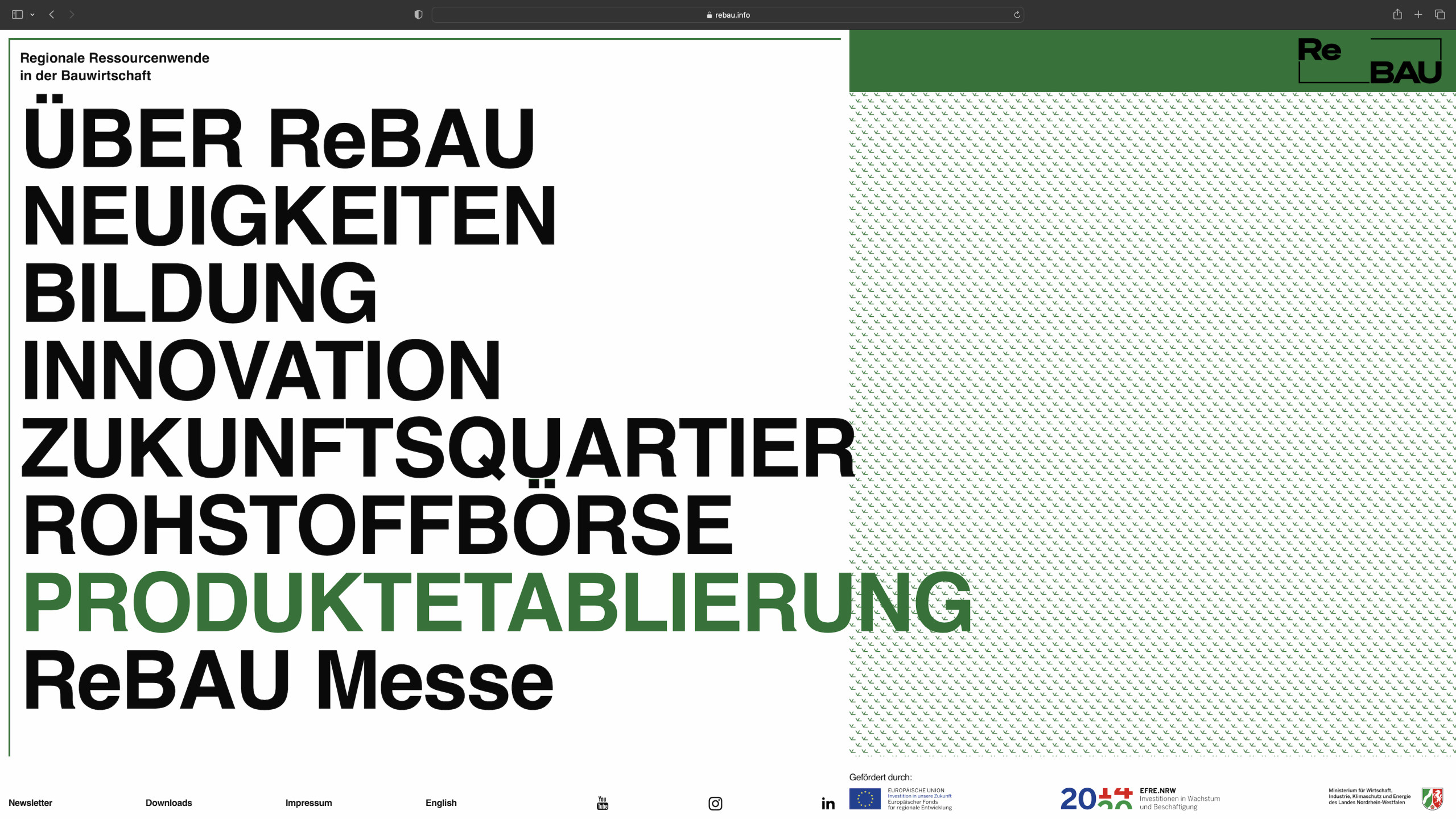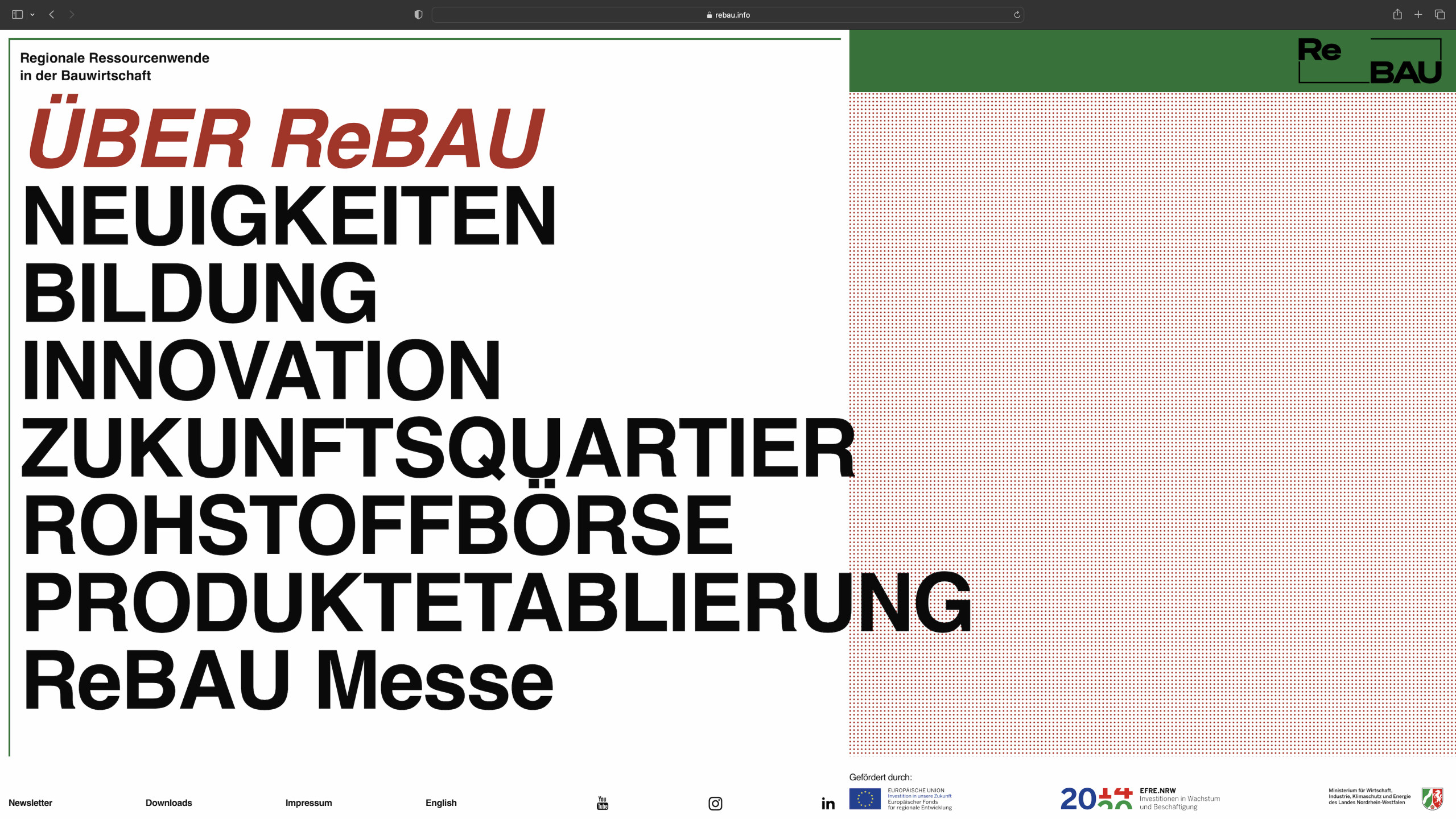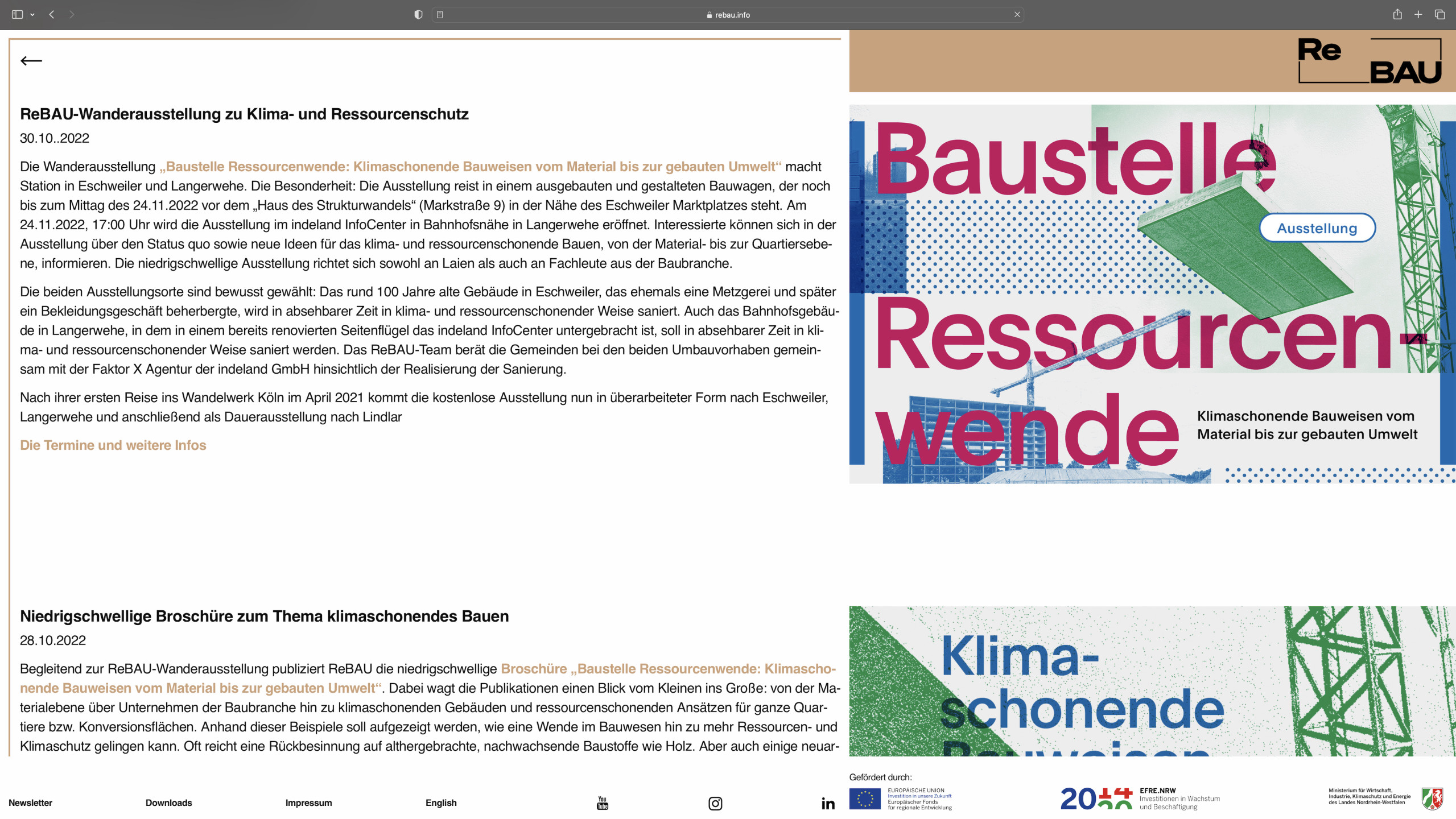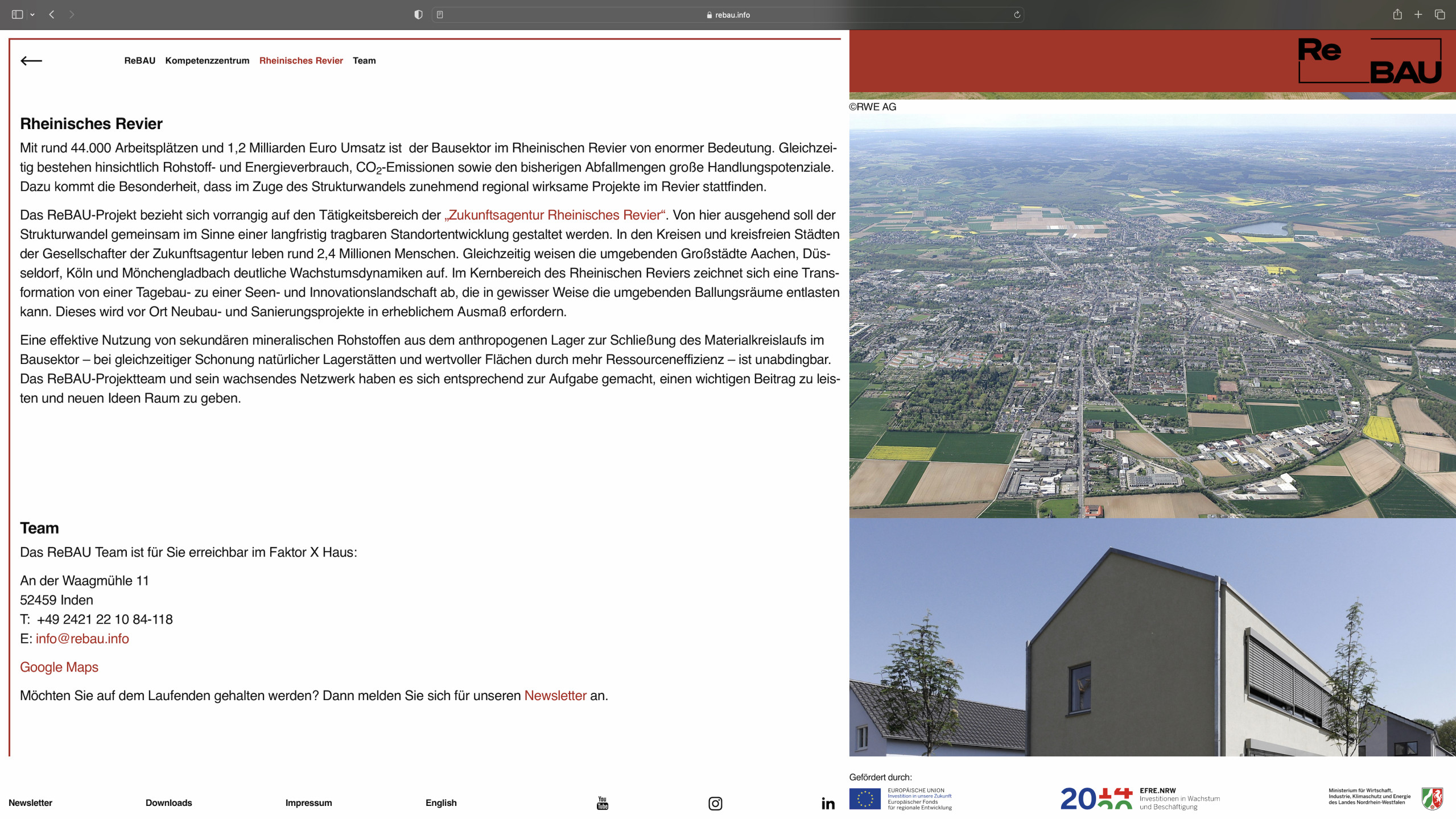
rebau.info
Webseite
ReBAU steht für Regionale Ressourcenwende in der Bauwirtschaft und beschäftigt sich mit einem umfassenden Ressourcen- und Klimaschutz im Bauwesen. Im Rahmen der neuen CI entstand auch eine Website. Die drei Hauptfarben unterstreichen die Idee der Nachhaltigkeit und Dringlichkeit. Zusätzlich werden Flurkarten verwendet, um sich visuell dem Bauwesen zu nähern. Die typographische Gestaltung ist durch geometrisch starke Formen geprägt.
Schrift: Work Sans von Google Fonts (Wei Huang)
& Söhne von Klim Type Foundry